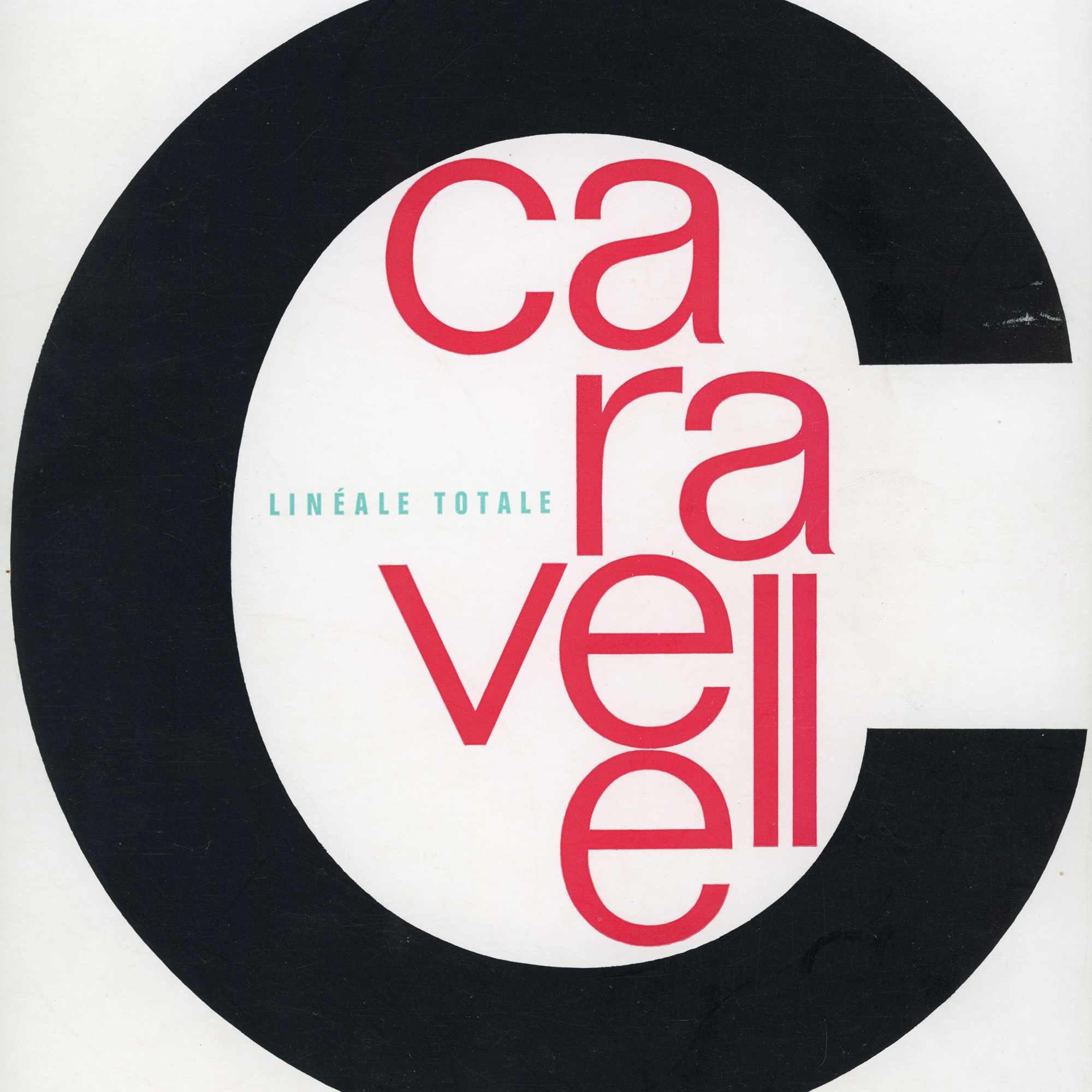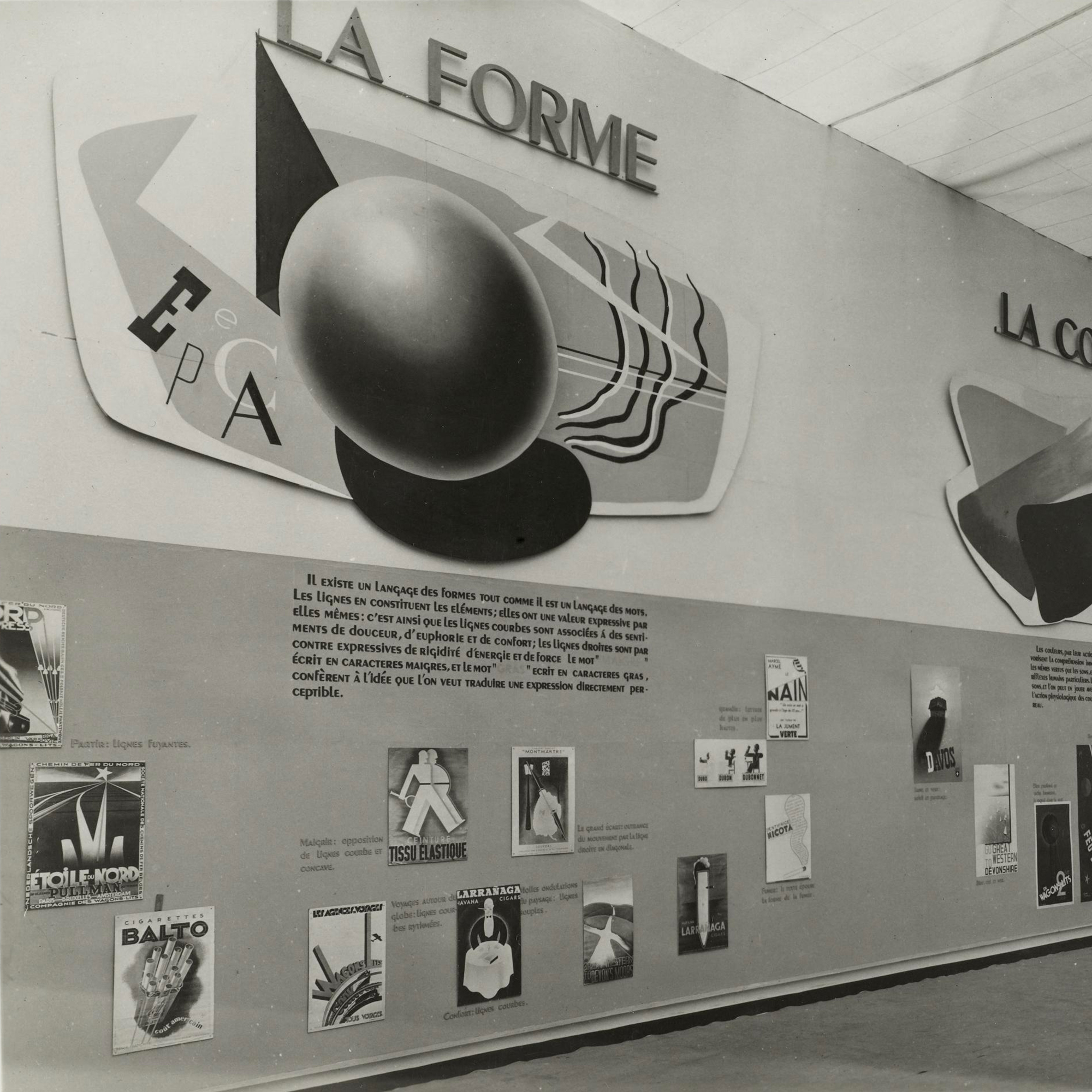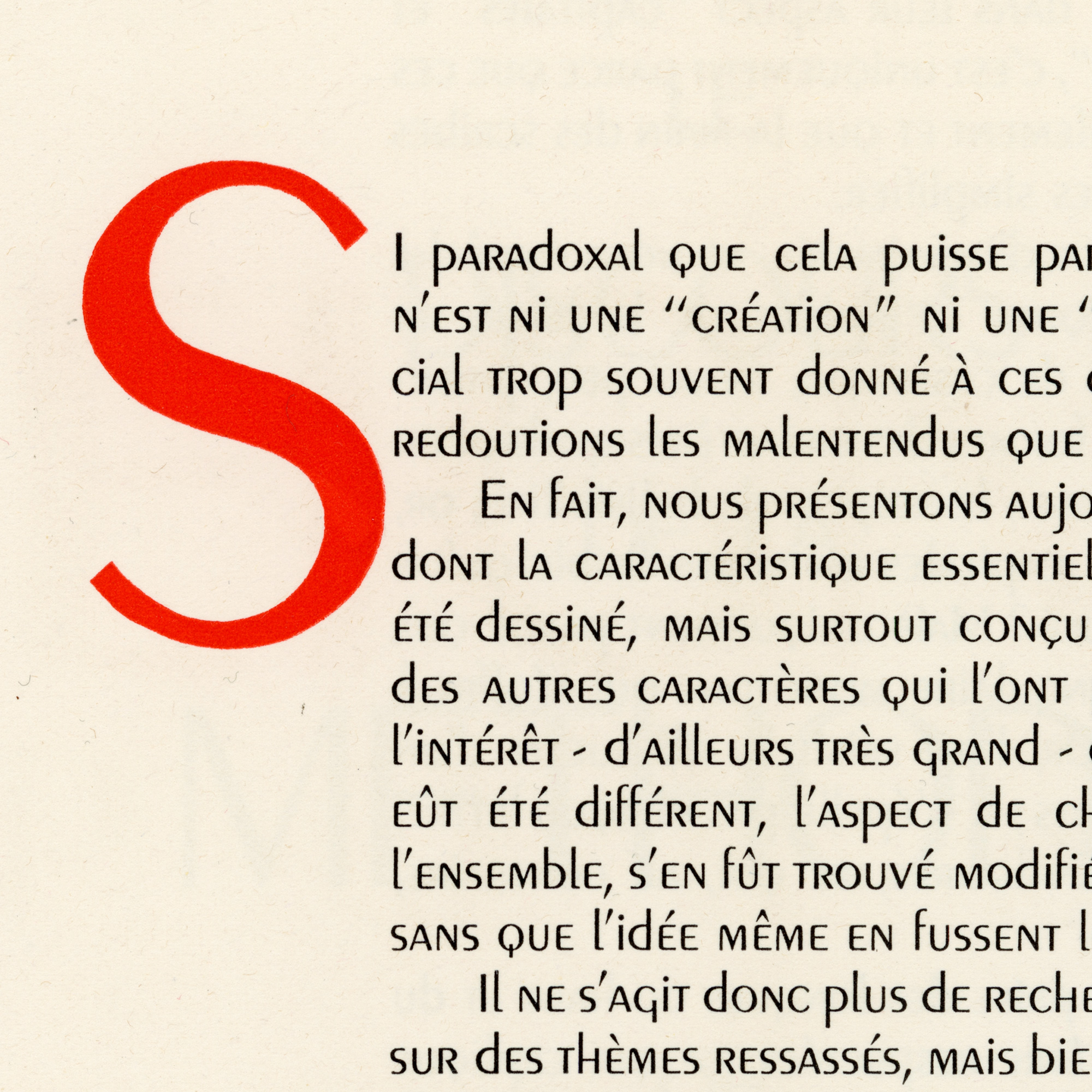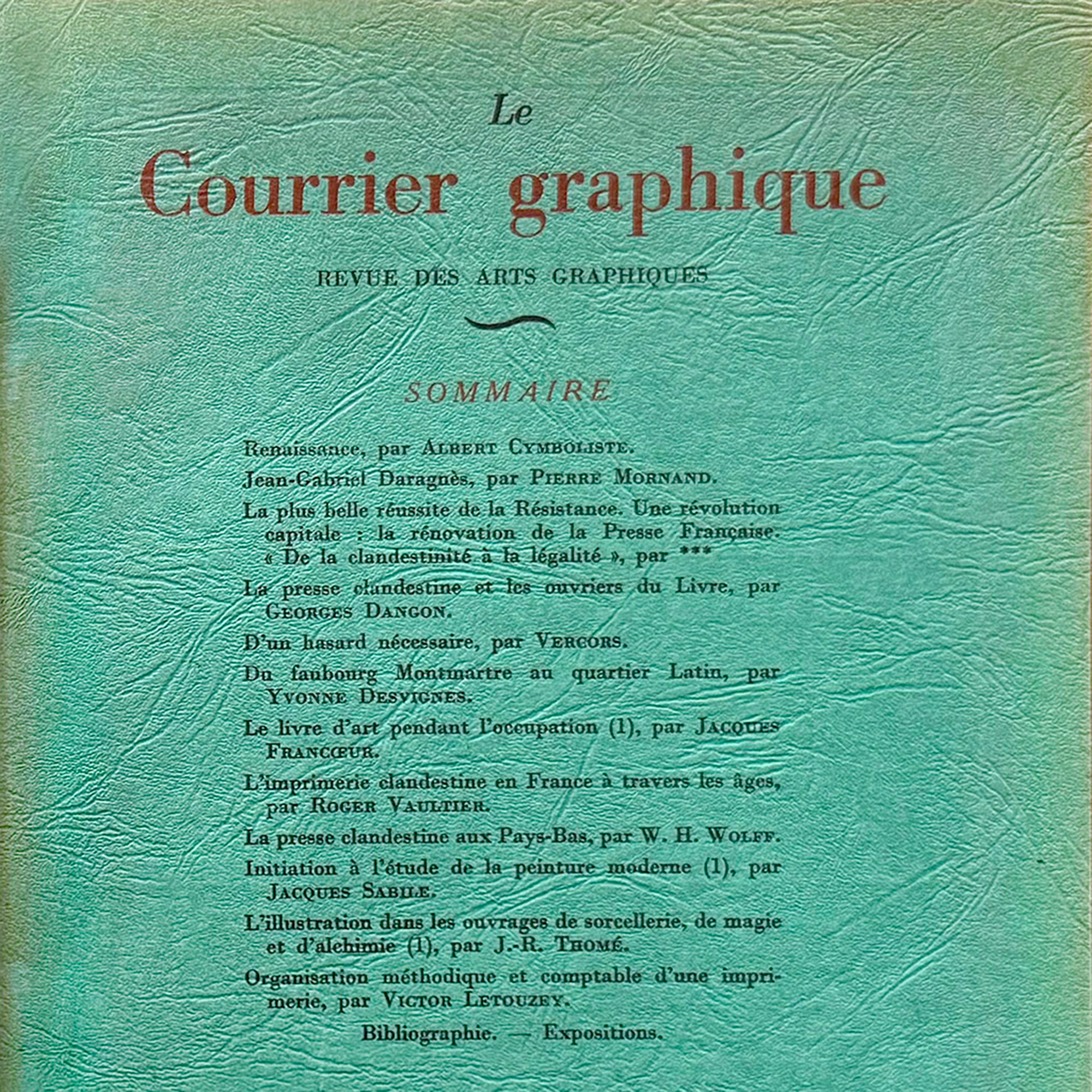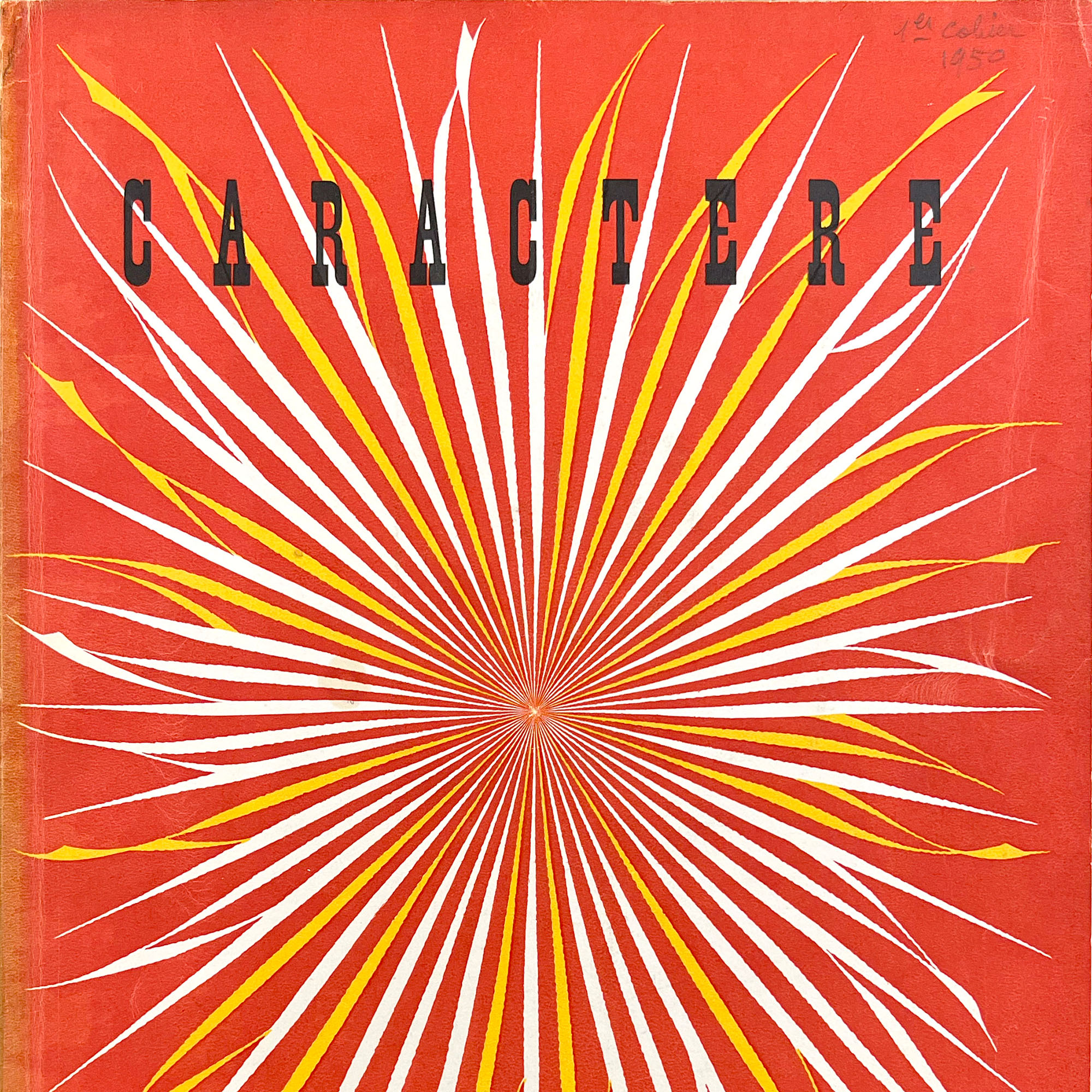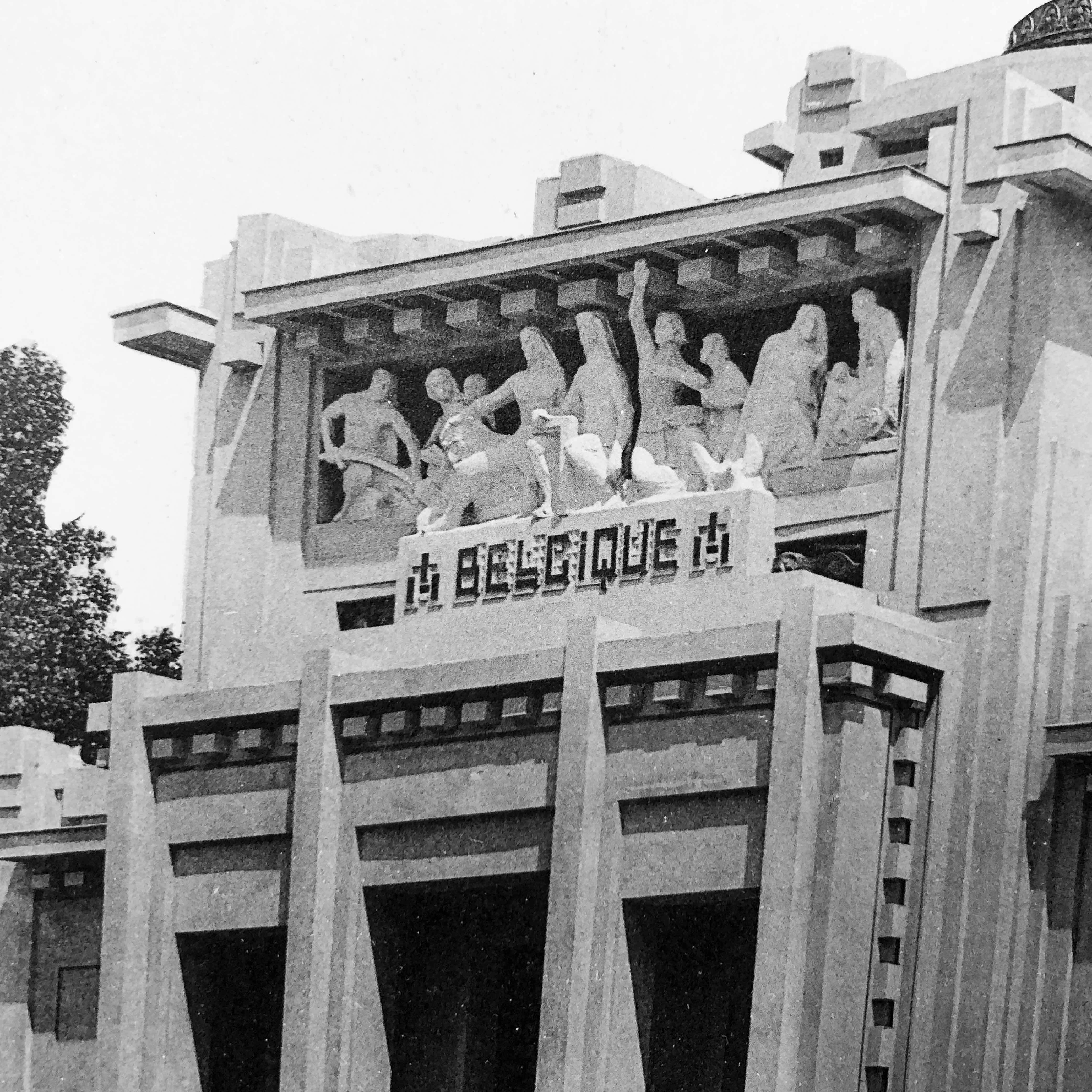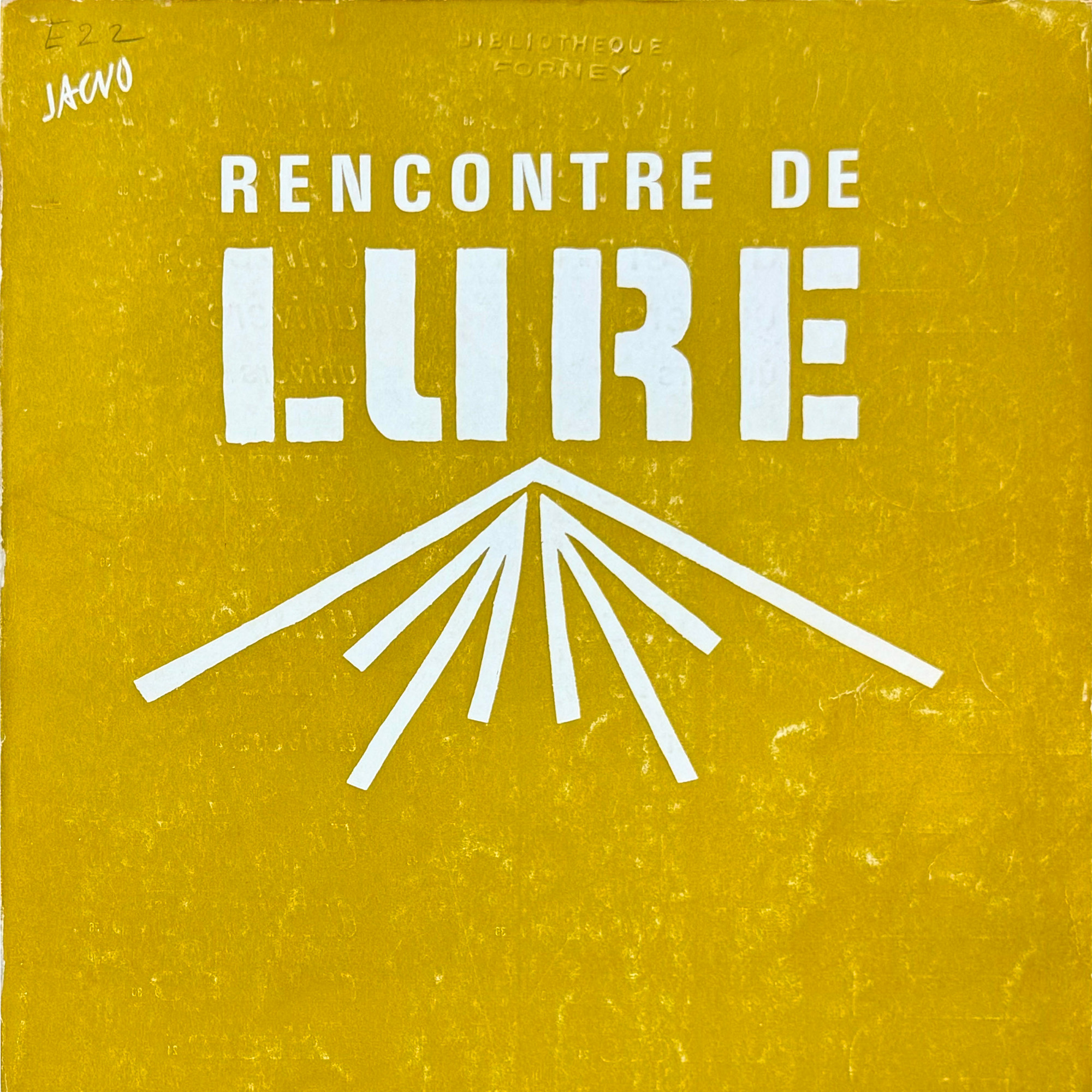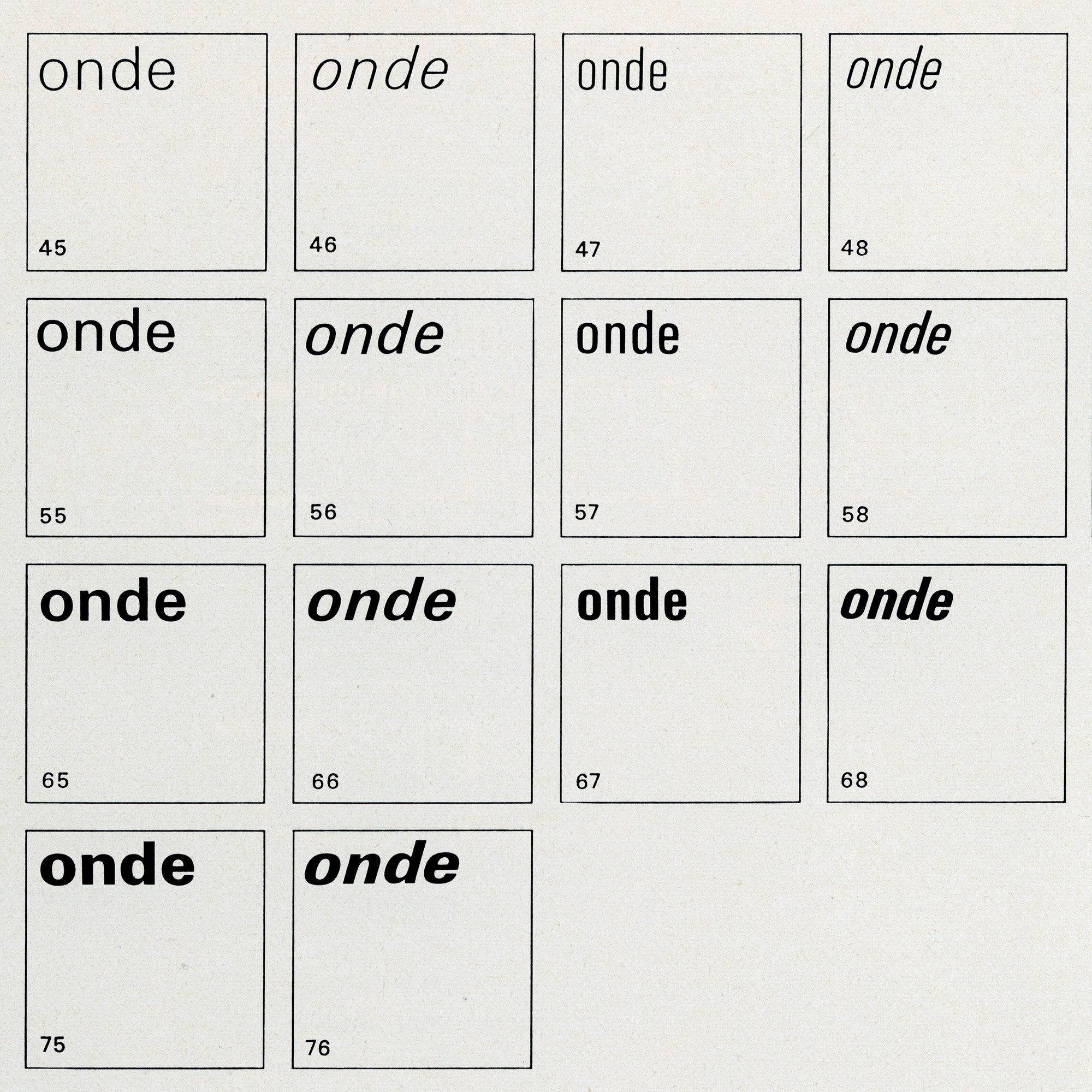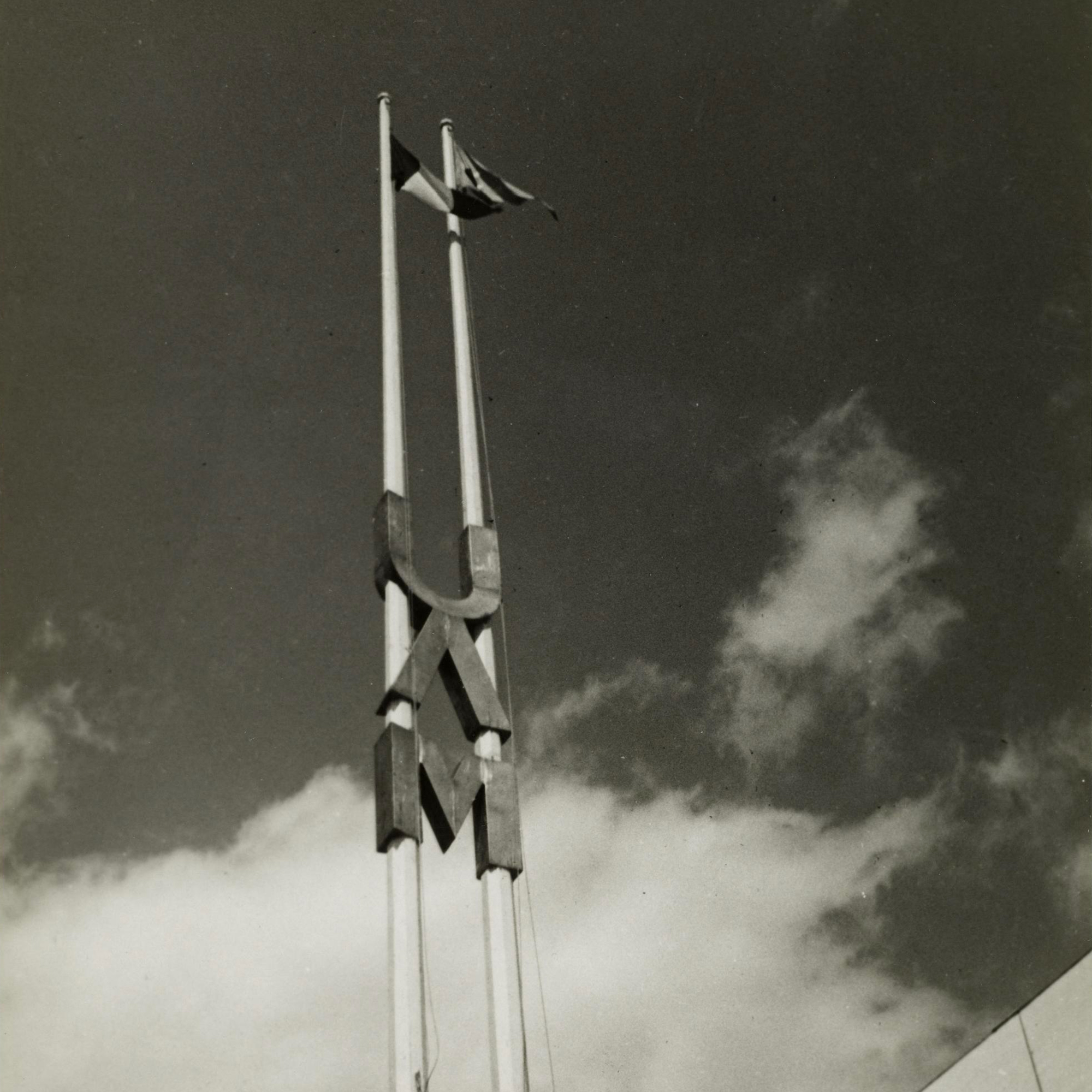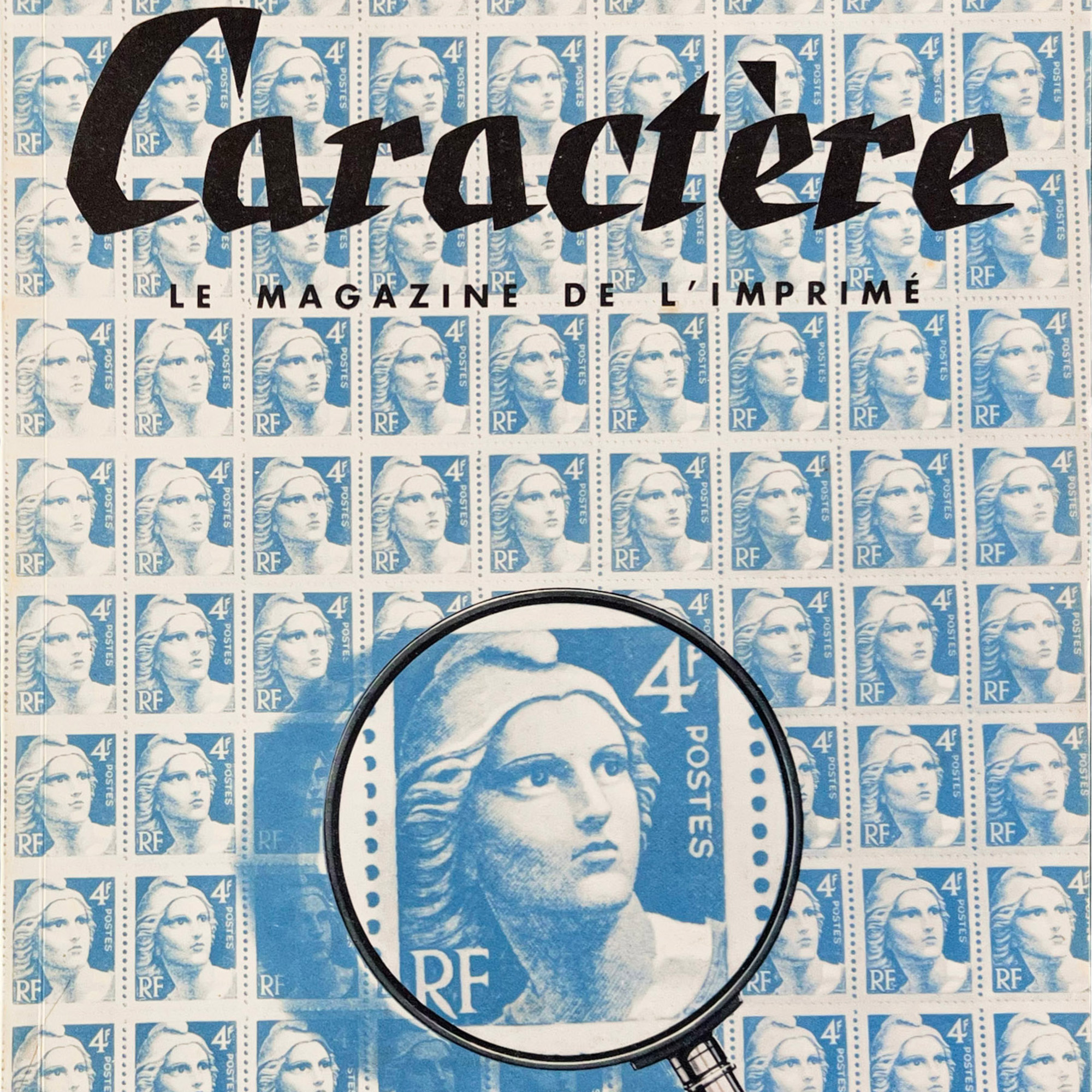
Réception de la Nouvelle Typographie dans les scènes graphiques francophones : rejets, adoptions, renégociations (1925–1979)
La
Nouvelle
Typographie
Techniques graphiques, couverture conçue par Marcel Jacno, numéro double 32-33, juillet-octobre 1960.
Détail du spécimen du Peignot, conçu par A. M. Cassandre, et publié par la Fonderie Deberny & Peignot, 1937.
Enseigne du pavillon de l'union des artistes modernes, Exposition internationale, Paris, 1937.